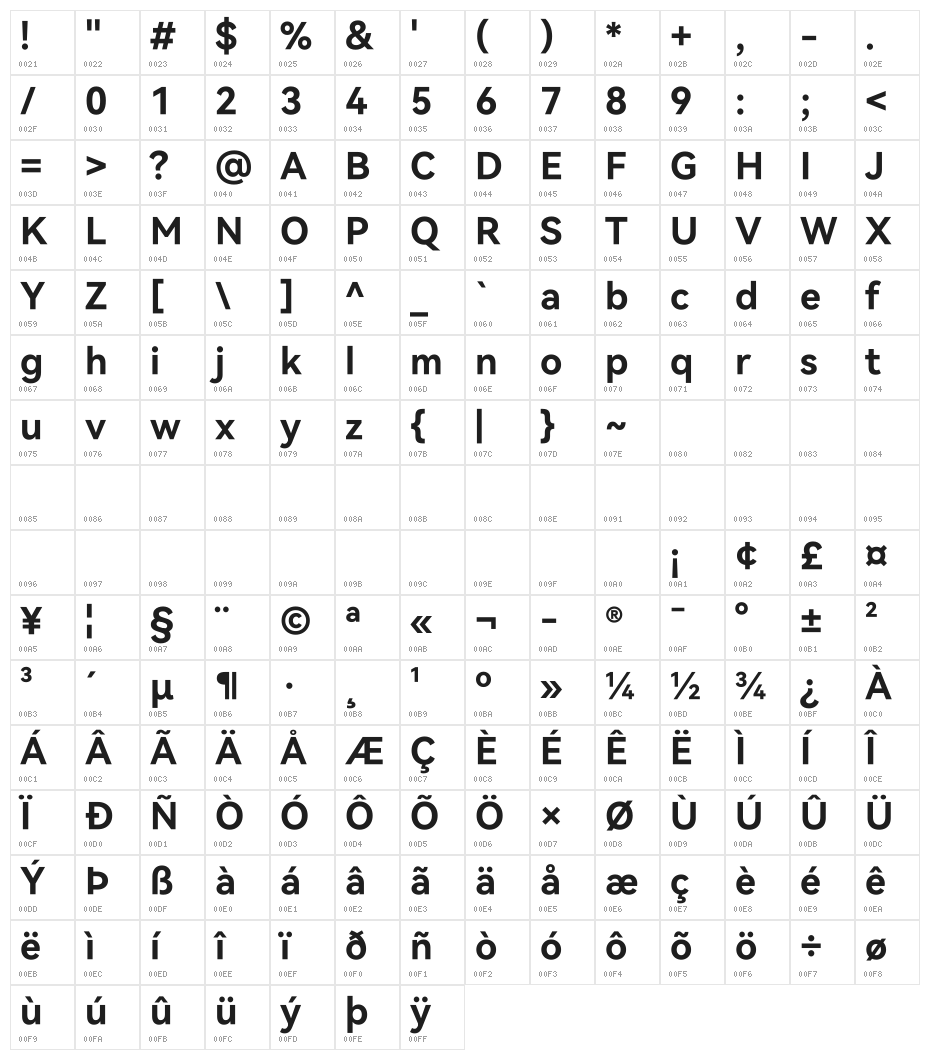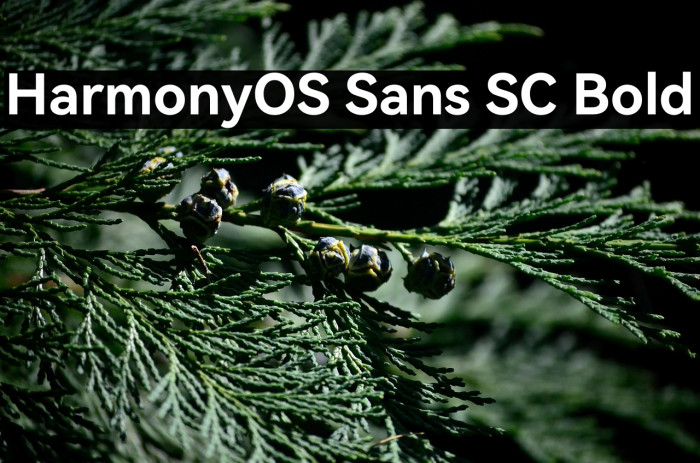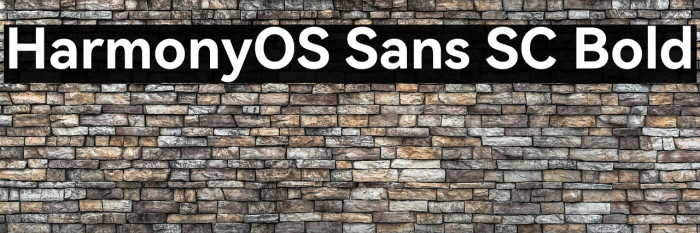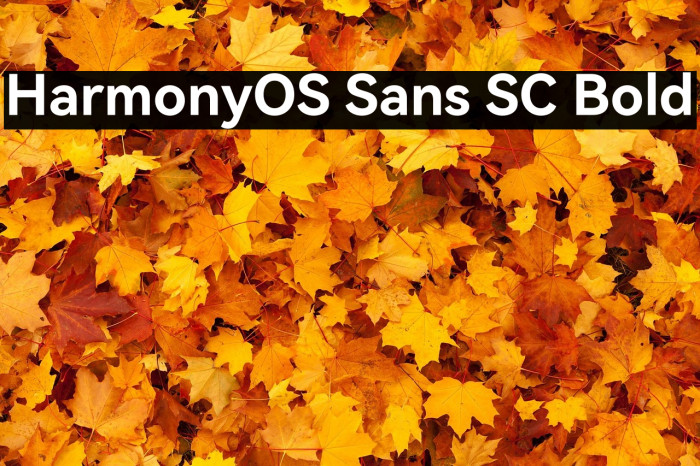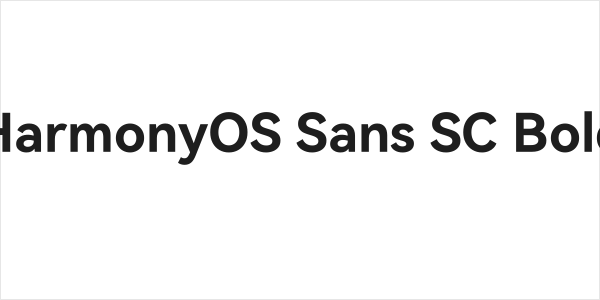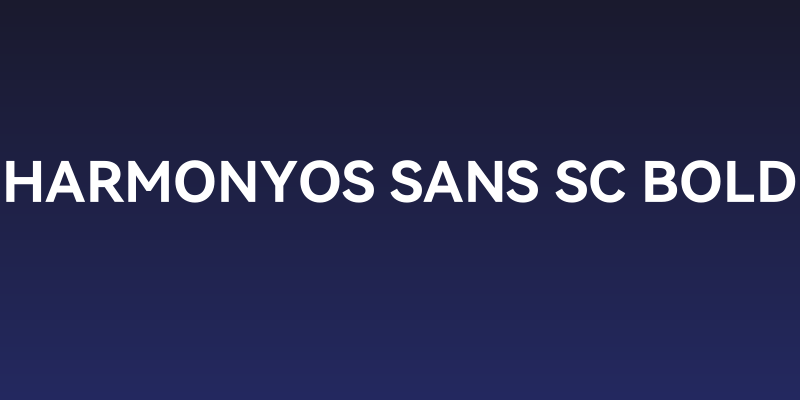
HarmonyOS Sans SC Bold Font
✎ Sans Serif
| 使用场景 | Headlines, Body text, Logos |
| 推荐项目 | Ideal for branding, advertising, web design, and user interfaces due to its clarity and modern appeal. |